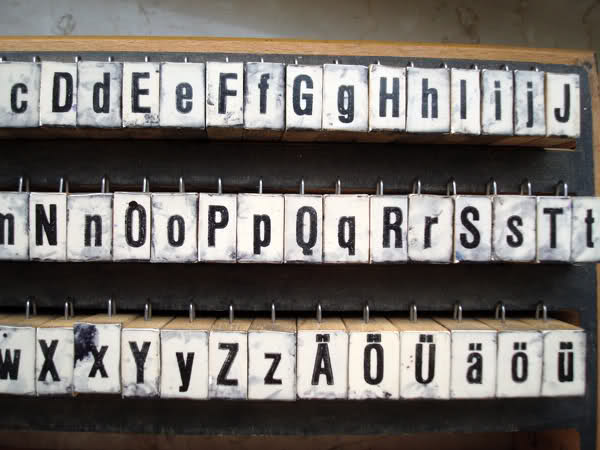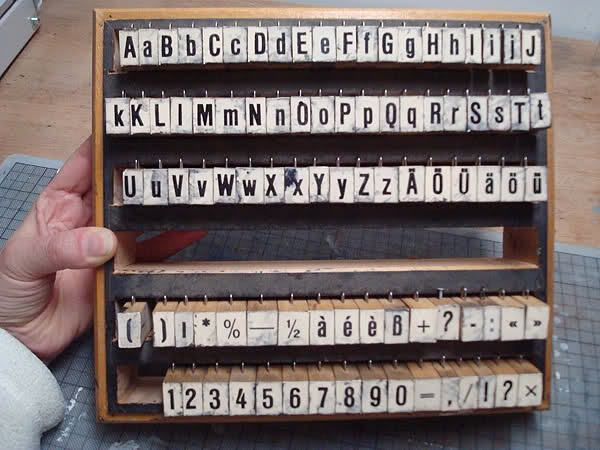
Neoprint Stempelsatz - welche Schrift?
Hallo zusammen, ich habe auf dem Flohmarkt einen Stempelsatz gekauft und wüße zu gerne, welche um welche Schrift es sich dabei handelt. Leider sind die Gummibuchstaben nicht mehr alle heile und ich überlege, ob ich mir neue Buchstaben dafür anfertigen lasse.
Ich frage mich, ob die Zahlen wirklich zu den Buchstaben gehören. Ich habe gerade mal ein bisschen recherchiert und alle Schriften, die zu den Buchstabenformen passen, haben eine geschlossene 4, bei Deinem Stempelsatz ist die Vier aber offen. Am dichtesten dran ist für mich die Monotype Grotesque Condensed, aber die Vier macht nicht mit…
Es handelt sich um die Commercial Grotesk der Haas'schen Schriftgießerei, die seit Ende der 50er Jahre als Helvetica schmalhalbfett im Programm bei Haas und der D. Stempel AG war.
Ja, die Commercial Grotesk halbfett könnte es sein. Hier habe ich ein Schriftblatt von E. Thiele gefunden, da ist sie drauf: http://www.klingspor-museum.de/Klingspo ... Thiele.pdf
Es heißt hier in dem PDF, die Schrift sei "Ende der 60er in die Helvetica-Familie als schmalhalbfett und schmalfett eingegliedert", aber täusche ich mich oder sieht die Helvetica schmalhalbfett nicht doch um einiges moderner/frischer aus, als die Commercial Grotesk halbfett, die ja wirklich so einen "Charme" der 40er hat.?
Um einzelne Stempel nachfertigen zu lassen, muß man nicht zwangsläufig die Schrift haben. Wenn es nicht zu viele sind, könnte man notfalls auch die Stempelabdrücke von der Rückseite reproduzieren und nachbearbeiten.